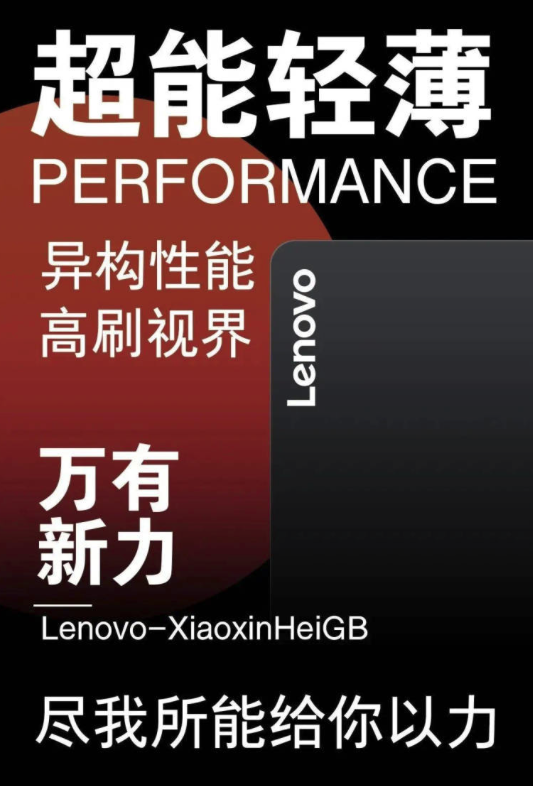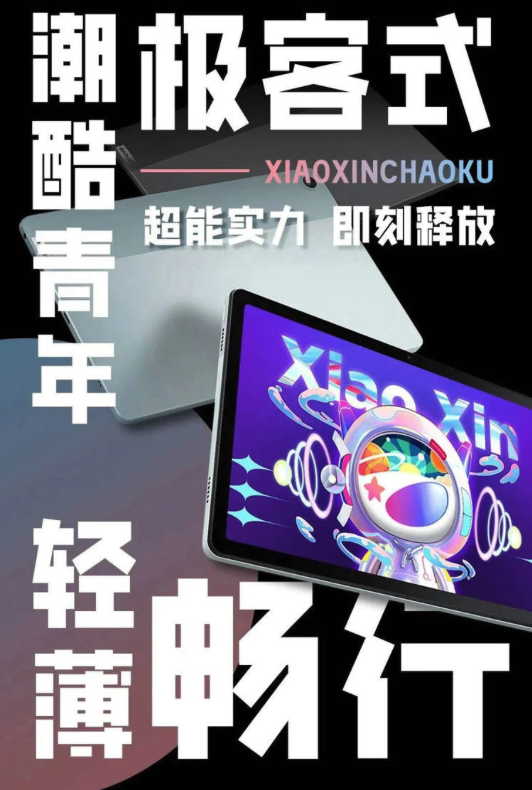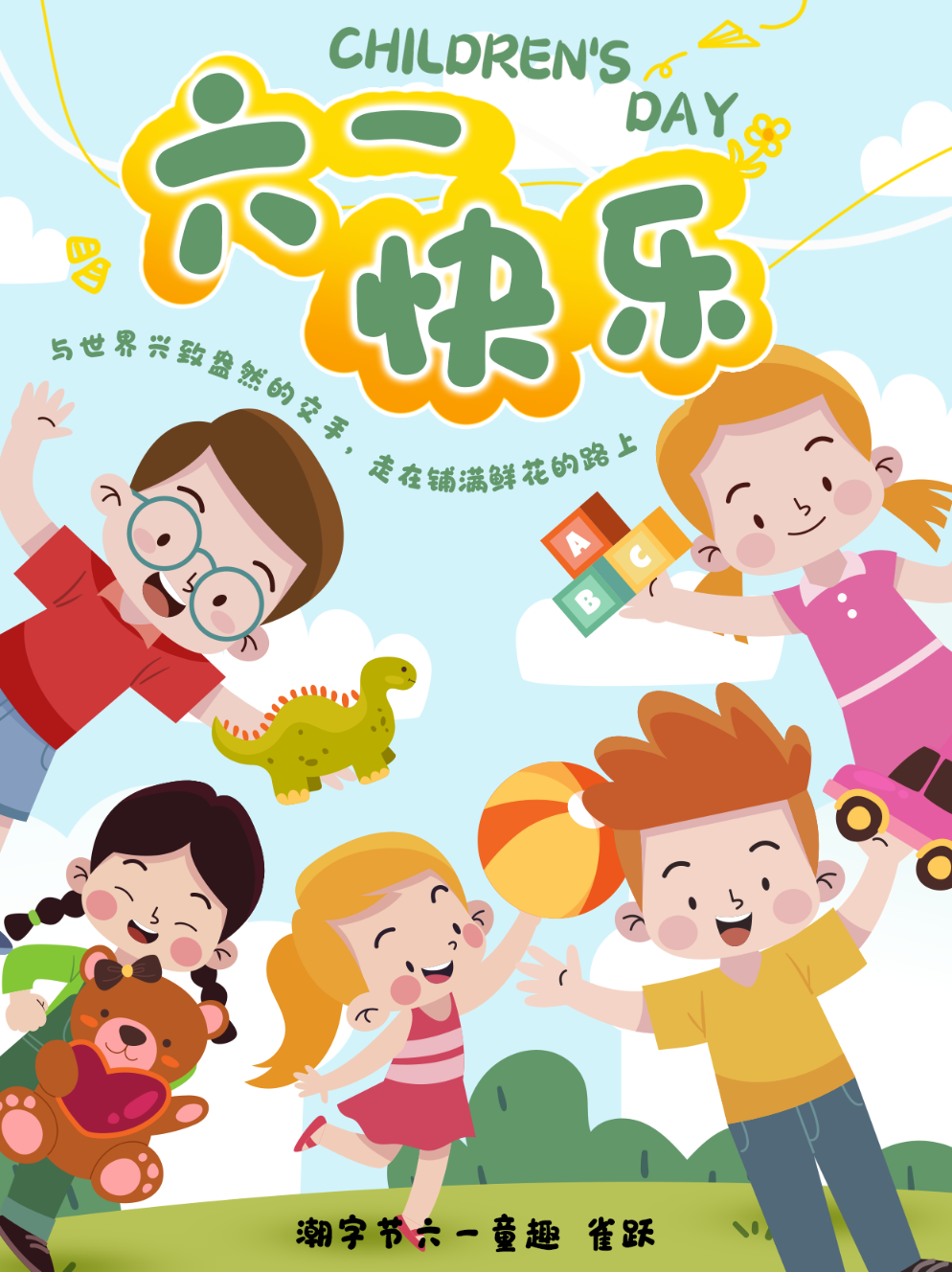
✨🎄圣诞氛围拉满!3款绝美字体让你的贺卡C位出道🎁✨
亲们,圣诞节🎅的脚步声越来越近啦!是不是已经开始琢磨着怎么给亲朋好友送上独一无二的祝福了呢?今天,就来揭秘3款超适合圣诞题材的字体宝藏,保证让你的贺卡、手账、社交媒体文案瞬间闪耀✨,成为朋友圈里最亮的那颗星!
1️⃣ 联想小新潮酷体 🎉
想要点不一样的圣诞风?联想小新潮酷体绝对是你的菜!它融合了现代简洁的元素,线条直率不失个性,用在圣诞寄语上,既显得时尚又不失节日的温馨。想象一下,“圣诞快乐”四个字,用它写出来,简直就是节日氛围的催化剂!🔥
2️⃣ 潮字节六一童趣 🎈
谁说大人不能实现愿望?在圣诞节,就让我们用潮字节六一童趣字体,找回那份纯真的快乐吧!这款字体圆润可爱,仿佛带着糖果的甜蜜,用在圣诞卡片上,无论是“愿你的世界永远色彩斑斓”还是“圣诞愿望全部实现”,都能让人会心一笑,感受到满满的童心与温馨。🍬
3️⃣ 联想小新黑体 🖋
经典永不过时!联想小新黑体以其简洁大方的设计,成为传递圣诞祝福的稳重之选。它的线条清晰,阅读舒适,无论是长段的圣诞故事还是简短的祝福语句,都能展现出一种低调的奢华感。用它书写“愿爱与和平伴随你左右”,简直是冬日里最温暖的告白。💖
赶紧挑一款你喜欢的,动手DIY你的圣诞惊喜吧!让这个圣诞节,因为你的用心,而更加难忘!🎅🎄